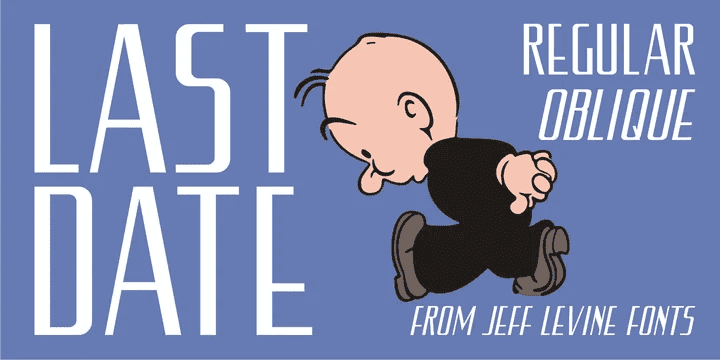
Типографская головоломка возникла с заголовком, написанным от руки на обложке песни 1919 года "I Am Always Building Castles in the Air".
Заглавная часть ["Castles in the Air"] представляла собой гибридную смесь из нескольких округлых букв в стиле модерн, но наряду с ними были и квадратные буквы с закругленными углами (отражающие грядущее движение ар-деко, которое должно было появиться еще через десятилетие).
Как полноценный алфавит, он не сочетался так хорошо, как в этих нескольких коротких словах. Что же делать? Было решено остановиться на квадратной форме, а более округлые символы оставить для будущего проекта.
В итоге получился Last Date JNL, доступный как в обычном, так и в наклонном вариантах.